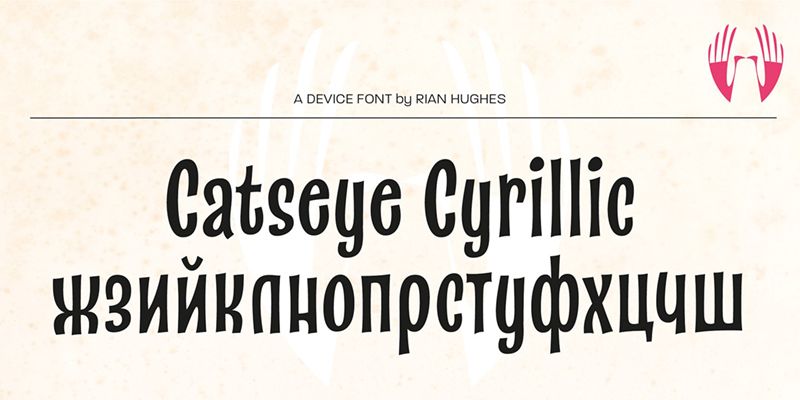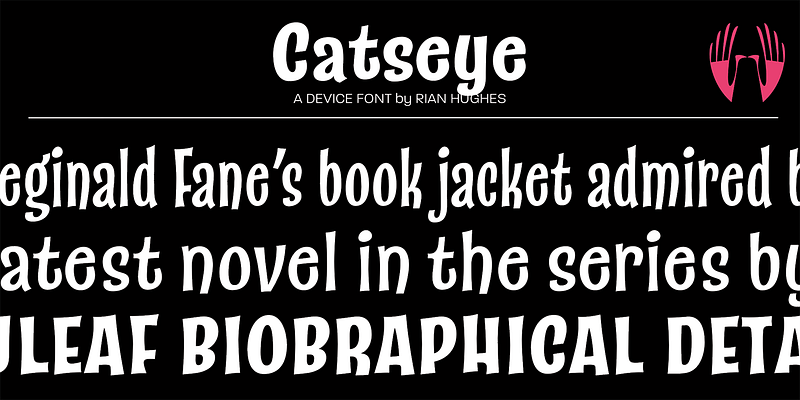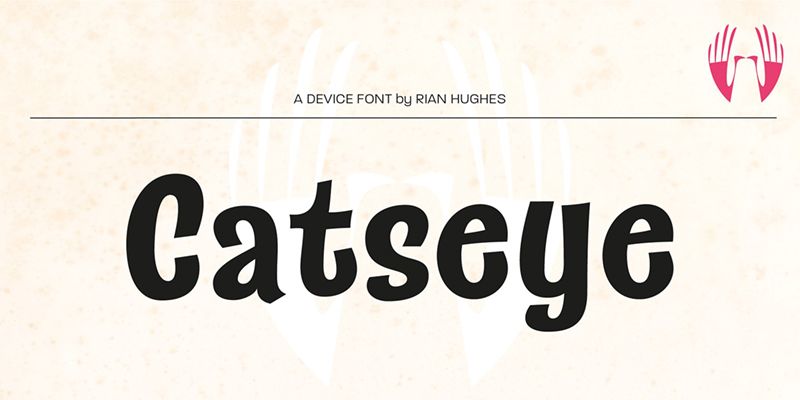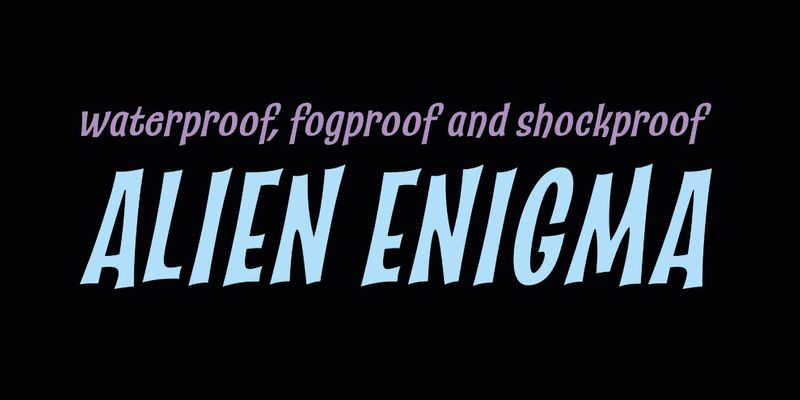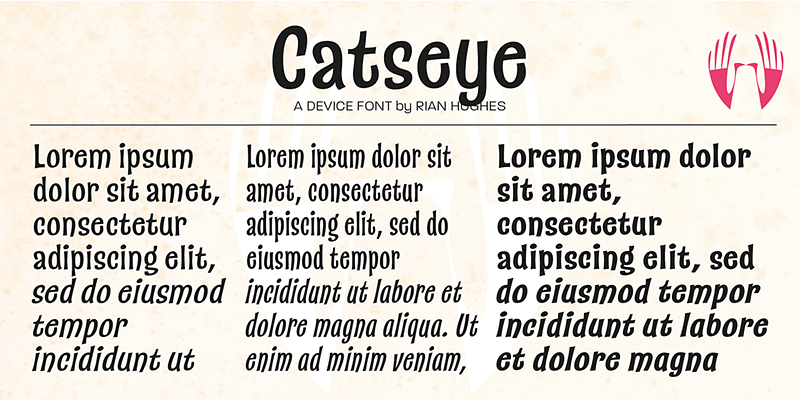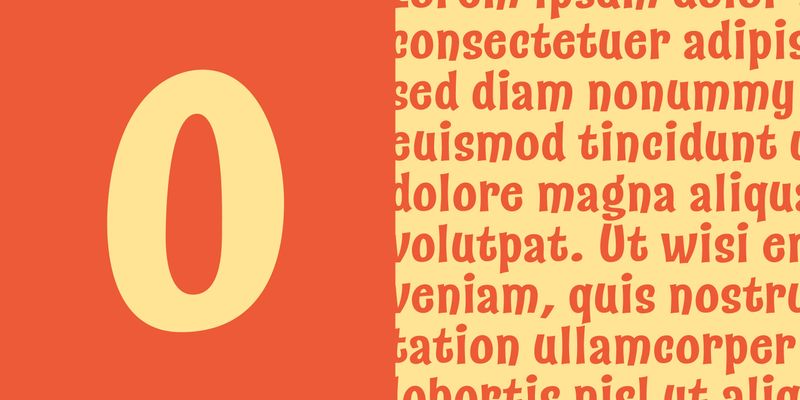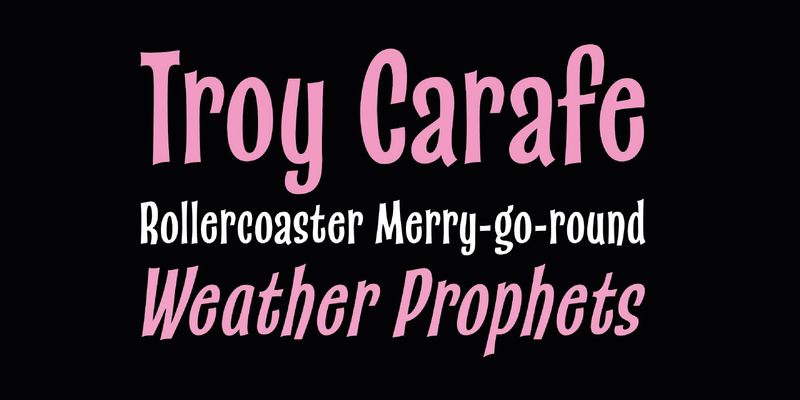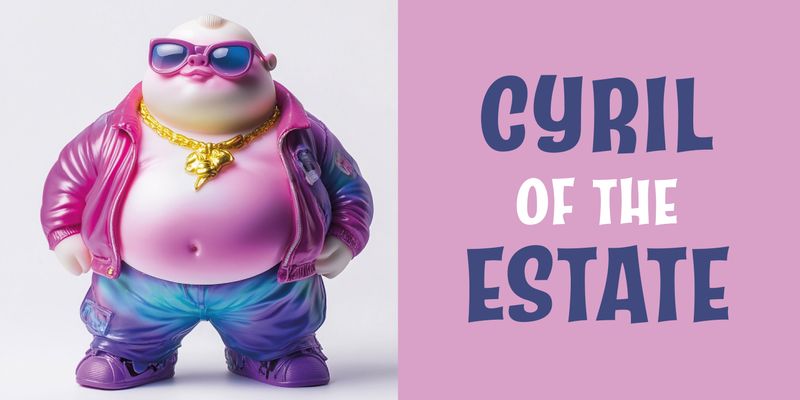
Une police sans empattement pleine d’entrain et librement dessinée, avec du caractère et du charme. Les graisses fines ont de l’élégance et celles plus grasses ajoutent du punch.